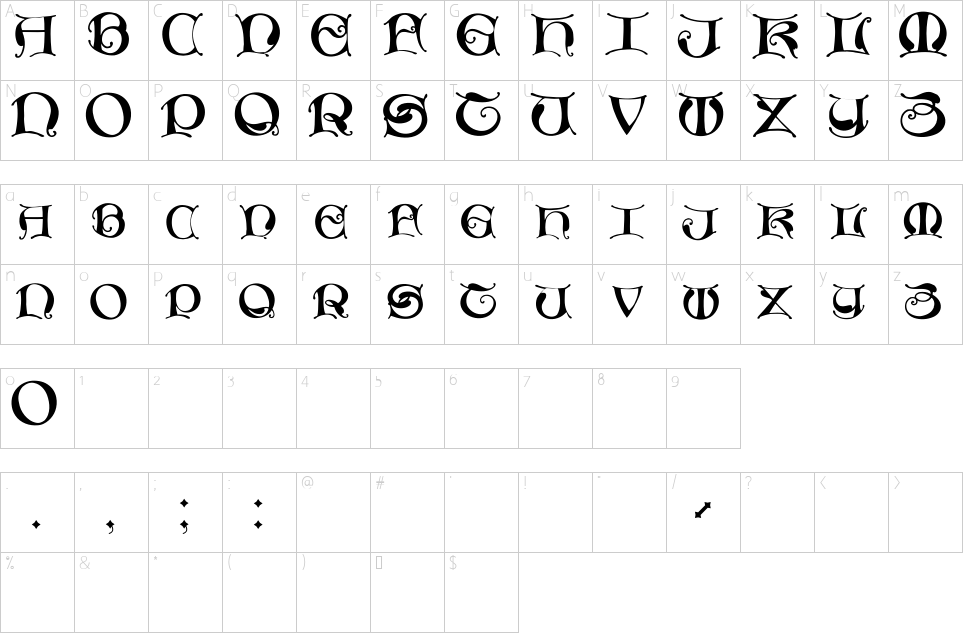
A fonte Missal Unciale Master é uma escolha perfeita para designers e amantes de gráficos que desejam adicionar um toque elegante e sofisticado a seus projetos. Desenvolvida pelo designer Manfred Klein 此处应有内容但并未提供,所以使用英文: Manfred Klein, a fonte tem uma aparência cuidadosamente elaborada e é perfeitamente adequada para títulos e textos de destaque em suas criações. Disponível tanto para Windows quanto para Mac, a Missal Unciale Master foi baixada 5. 697 vezes. Para quem busca graciosidade e refinamento, esta fonte é um excelente investimento. Se você está buscando uma fonte única e de alta qualidade para seu próximo projeto, Missal Unciale Master é uma fonte que você não pode perder.